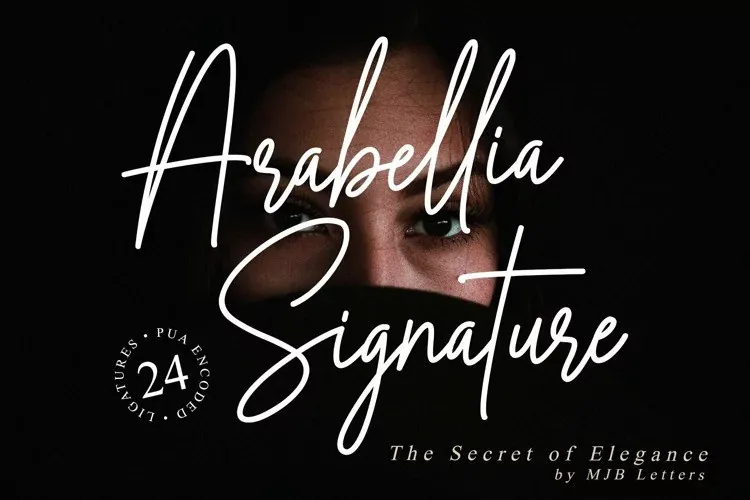
Arabellia Signature Font – Download Grátis
A fonte ‘Arabellia Signature Font’ é perfeita para aqueles que buscam uma sensação elegante e sofisticada no seu design. Ela se destaca como uma escolha profissional, especialmente quando se trata de escrita manuscrita. Esta fonte tem o potencial de dar um toque único a qualquer projeto, seja ele fashionista ou tradicional, desde marcas icônicas até a personalização dos mais detalhistas e delicados. O designer 99designs nos apresentou uma opção que destaca sua elegância através do uso profissional da escrita manuscrita. Suavidade e classe são as principais características desta fonte, oferecendo um aspecto incrivelmente estiloso. Com sua versatilidade para vários usos, este script é perfeito tanto para design de marca ou criação de logomarca quanto para o conceito de uma identidade visual que atinja todos os públicos. É ideal para projetos relacionados à moda e à criação de uma personalização única para qualquer evento especial, incluindo casamentos. Obrigado por escolher a ‘Arabellia Signature Font’! Seja ele um projeto casual ou elaborado, essa fonte é uma excelente opção para dar um toque único ao seu design.